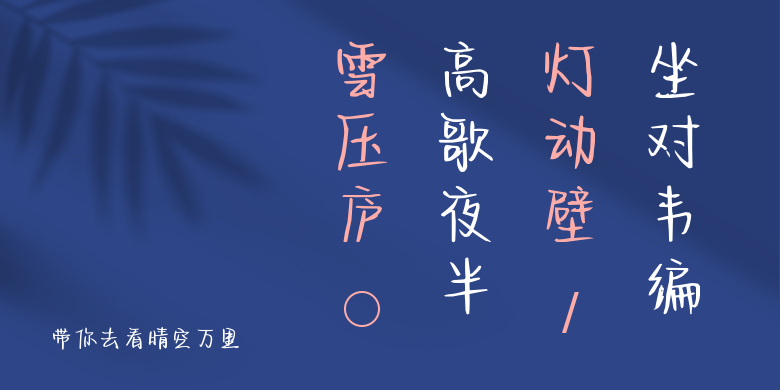
带你去看晴空万里
带你去看晴空万里,这款字体结构工整、笔画清晰,兼顾美观与易读性,适用于标题、正文、海报、包装、LOGO 等多种场景。字形优雅稳定,风格百搭耐看,适配日常排版与创意设计,让文字呈现更舒适、更具质感。带你去看晴空万里一笔一画,皆是细节,以均衡的比例、流畅的线条打造舒适视觉体验,字形端正大气,风格简约现代。无论是商业设计、品牌宣传还是日常排版,都能轻松驾驭,让文字更有格调与力量。带你去看晴空万里字体下载。